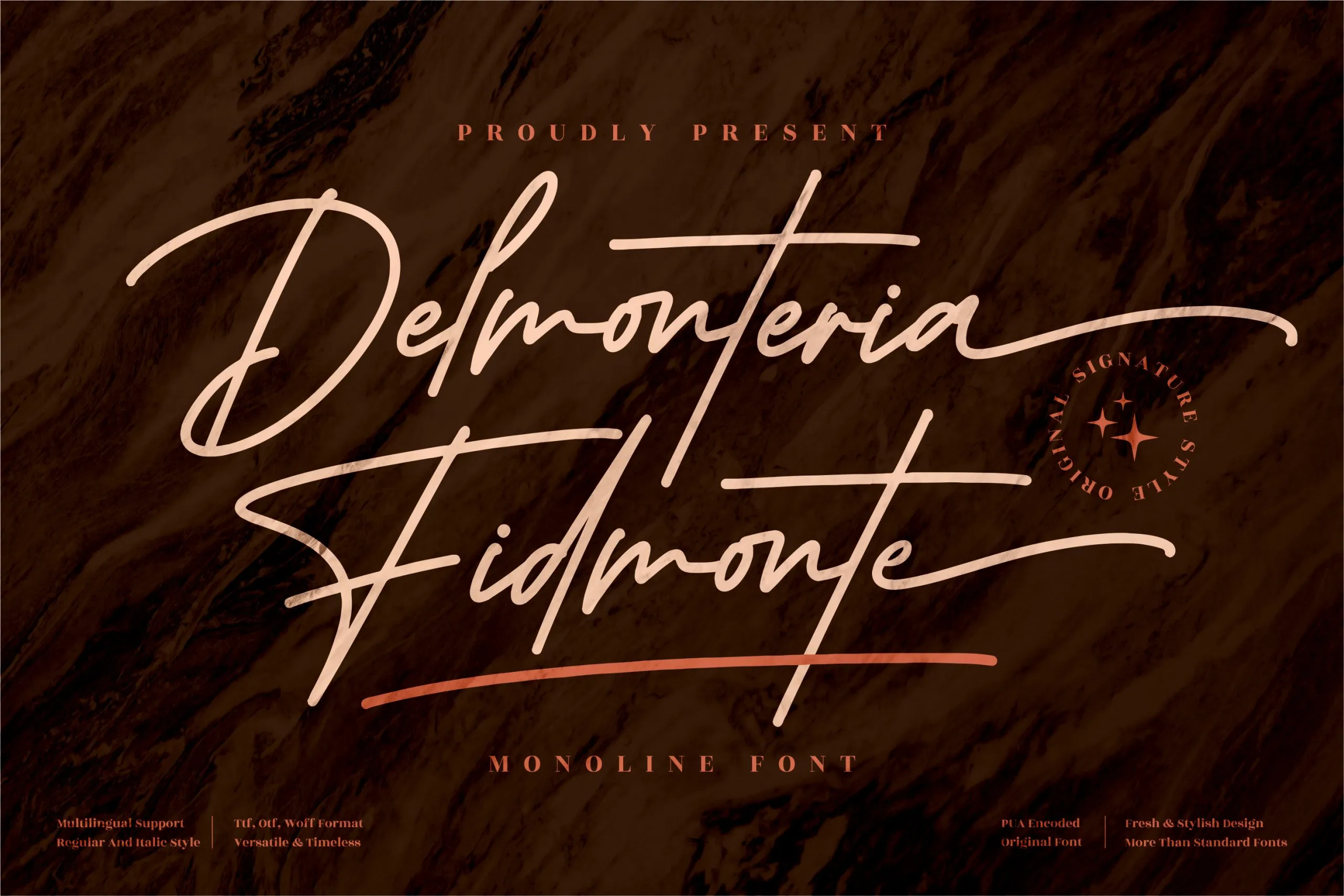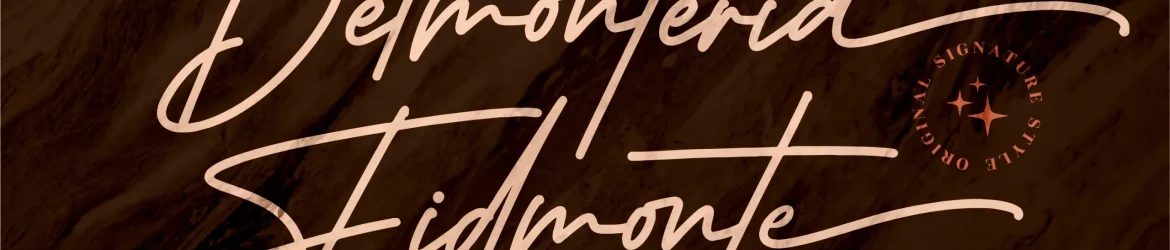
A Delmonteria Fidmonte Font é uma elegante fórmula de linhas monolineares criada por Perspectype Studio, ideal para qualquer projeto que desejemos dar um toque personalizado e sofisticado. Suas linhas finas e bem definidas são perfeitas para logotipos, projetos de identidade visual, designs de móveis, embalagens de produtos, bandejas de café, postais, cartões de visita e até mesmo capas de livros. Este font é especialmente apropriado quando buscamos um acabamento luxuoso em qualquer tipo de projeto, seja uma etiqueta ou até mesmo uma imagem fotográfica ou um papel de alumínio usado como um marco. Adicionalmente, sua simplicidade e elegância também permitem quebrar as regras do design, transformando simples mensagens em texturas memoráveis. É perfeito para adicionar o toque diferenciado aos seus projetos pessoais ou profissionais. Uma fonte desta qualidade é uma forma sutil de mostrar seu comprometimento com a qualidade e os detalhes finos que tornam um projeto único. A Delmonteria Fidmonte Font é perfeita para qualquer empreendimento que busca dar um toque diferenciado aos seus materiais digitais ou impressos.